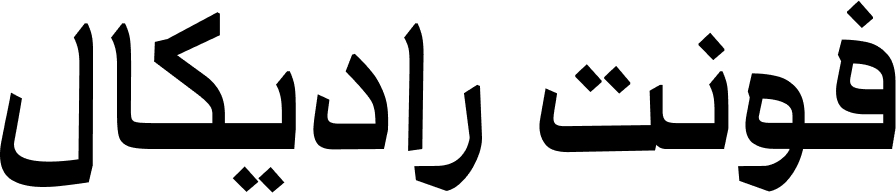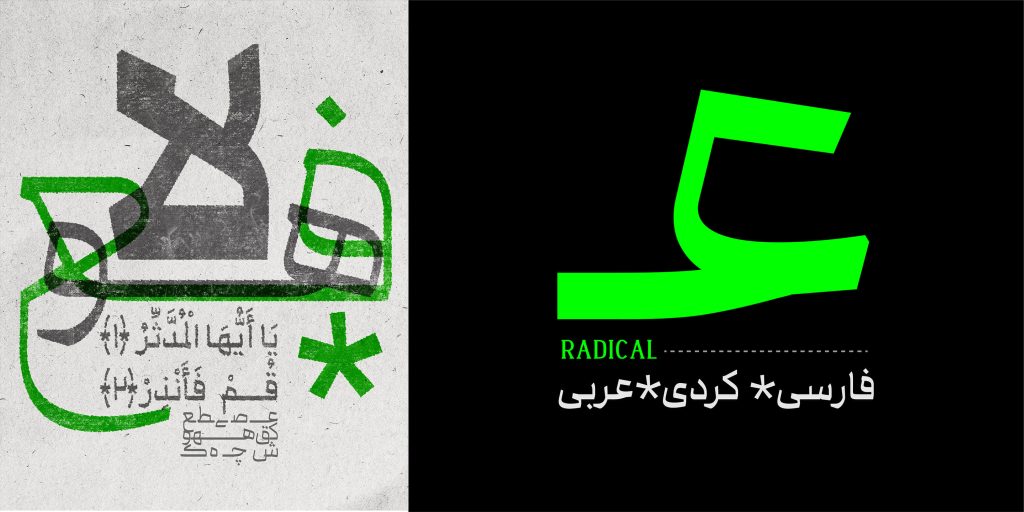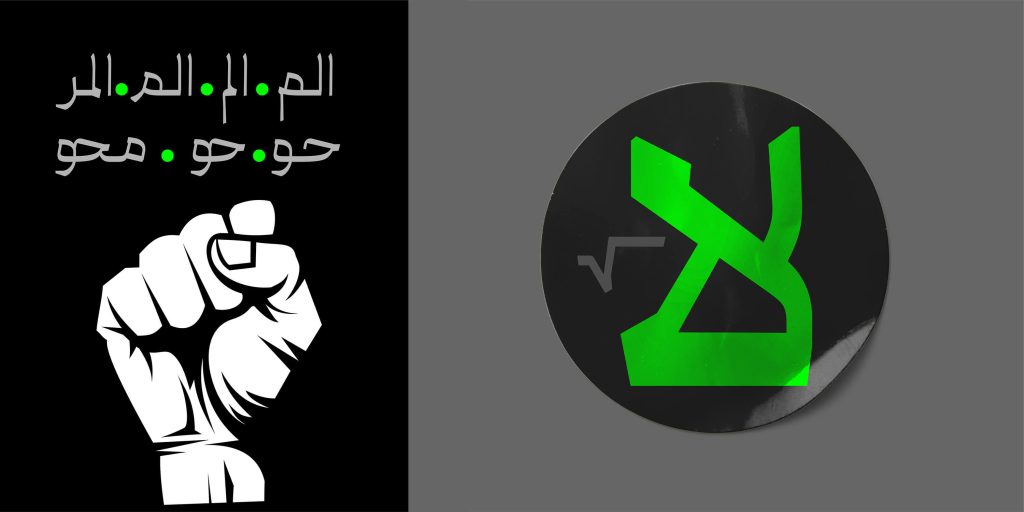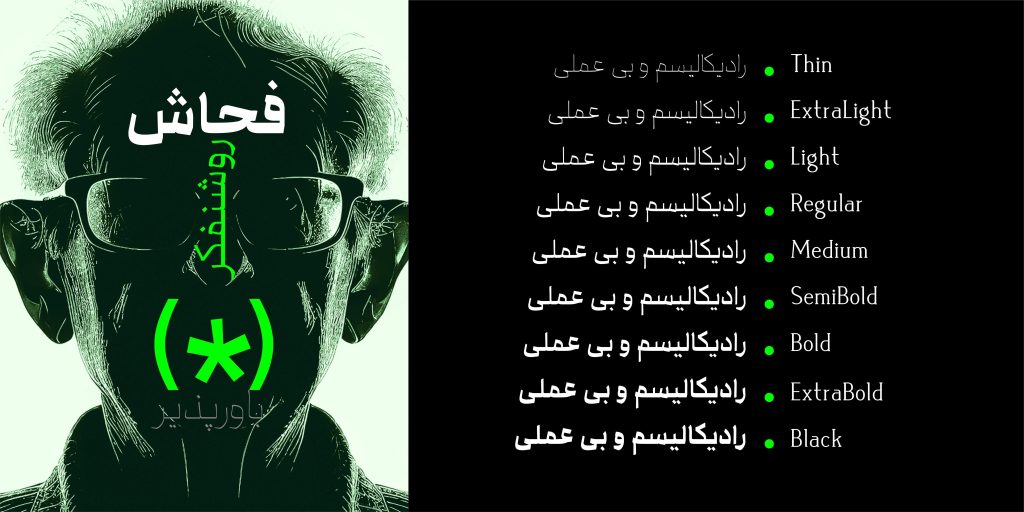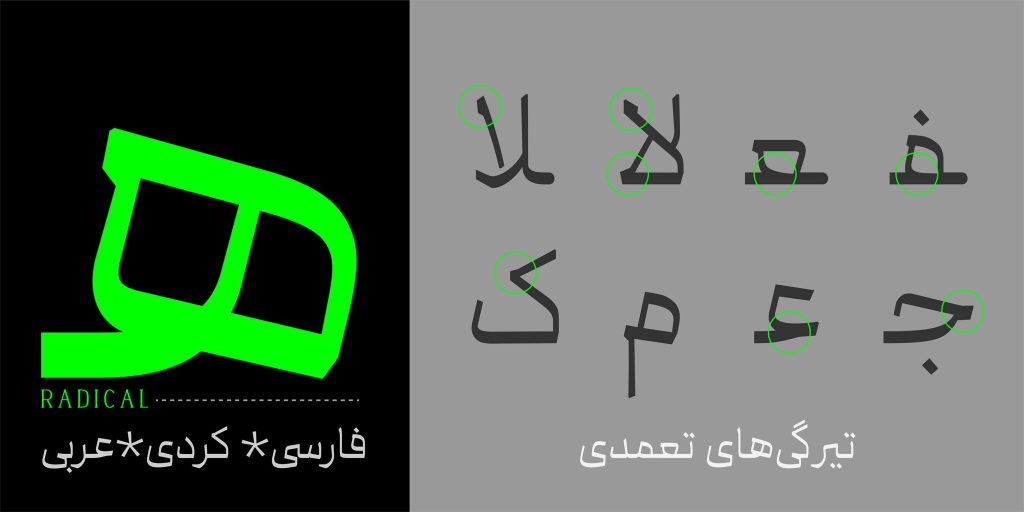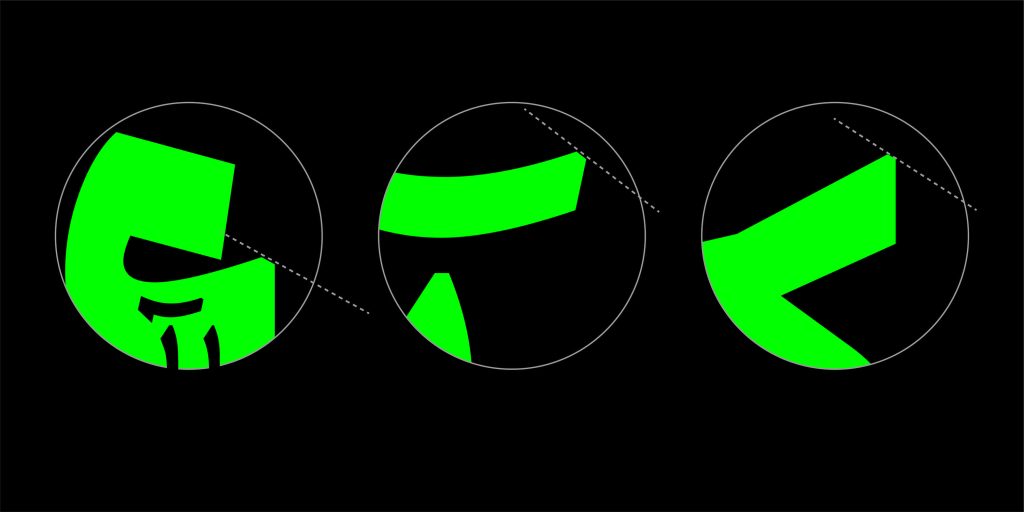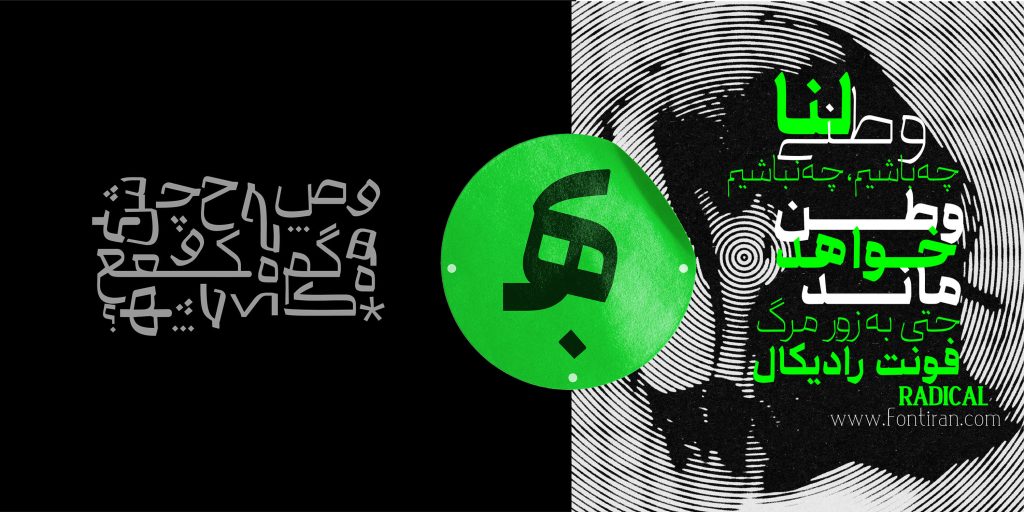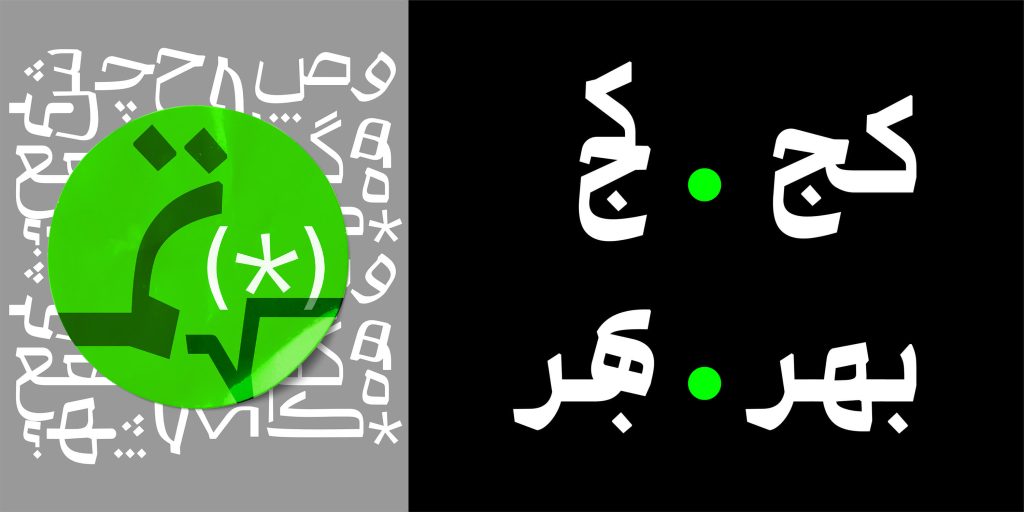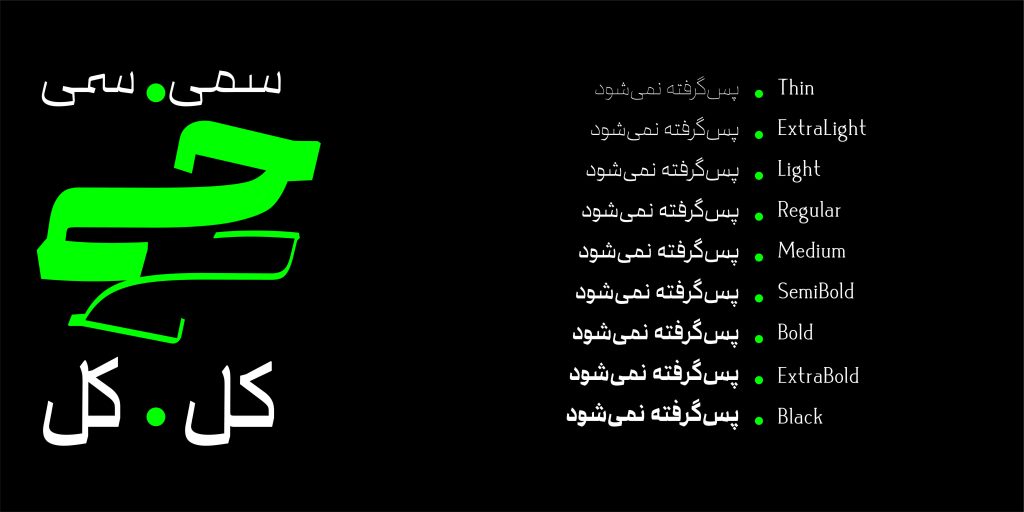
تایپ فیس رادیکال، قلمی با پیچ و قوسو شکستگی های فراوان می باشد. رادیکال از دسته فونت های هندسی است که مناسب برای پوستر و فضاهای تبلیغاتی می باشد.
فونت نمایشی رادیکال
اگر به دنبال قلمی نمایشی هستید فونت رادیکال دارای ویژگی نمایشی می باشد .با دارا بودن کنتراستی در سطح که تنه‌ی حروف دارای ضخامت تقریبا دو برابری حد معمول قلم است، گویی تمام حروف را در بندخط کرسی اصلی نگه می‌دارد اما با فاصله گرفتن از آن حرکات قلم آزادتر و رادیکال‌تر می‌شوند.
ایجاد تیرگی‌های عمدی و حتی ضخامت‌هایی غیر معمول از جمله ویژگی‌های رادیکال است که باعث منحصر به‌فرد بودن و هم‌چنین تمایز آن می‌شود. رادیکال صریح، جدی و رو راست است که مستقیم به اصل ماجرا می‌پردازد  و خواننده را به حاشیه نمی برد.
پشتیبانی از اوزان مختلف
می‌توان با آن هر حرفی را بی‌پرده زد.
نسخه اولیه این فونت در ۹ وزن ارائه شده است :
Thin-Extralight-Light-Regular-Medium-SemiBold-Bold-ExtraBold-Black
زبان‌های پشتیبانی شده :
فارسی , عربی، کوردی
9 وزن